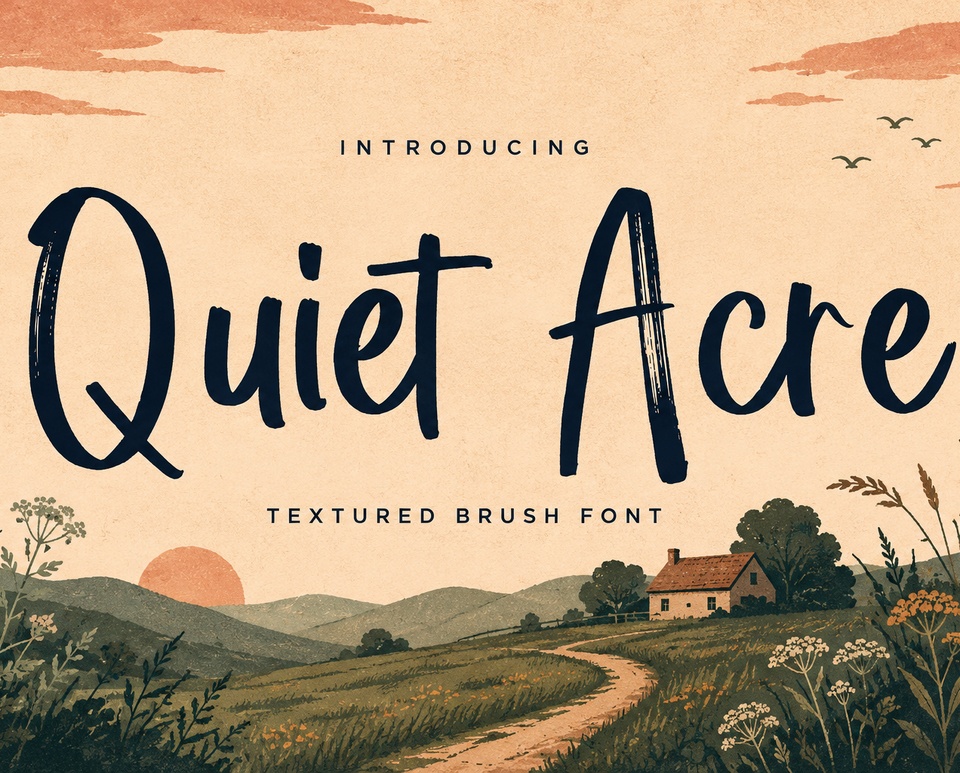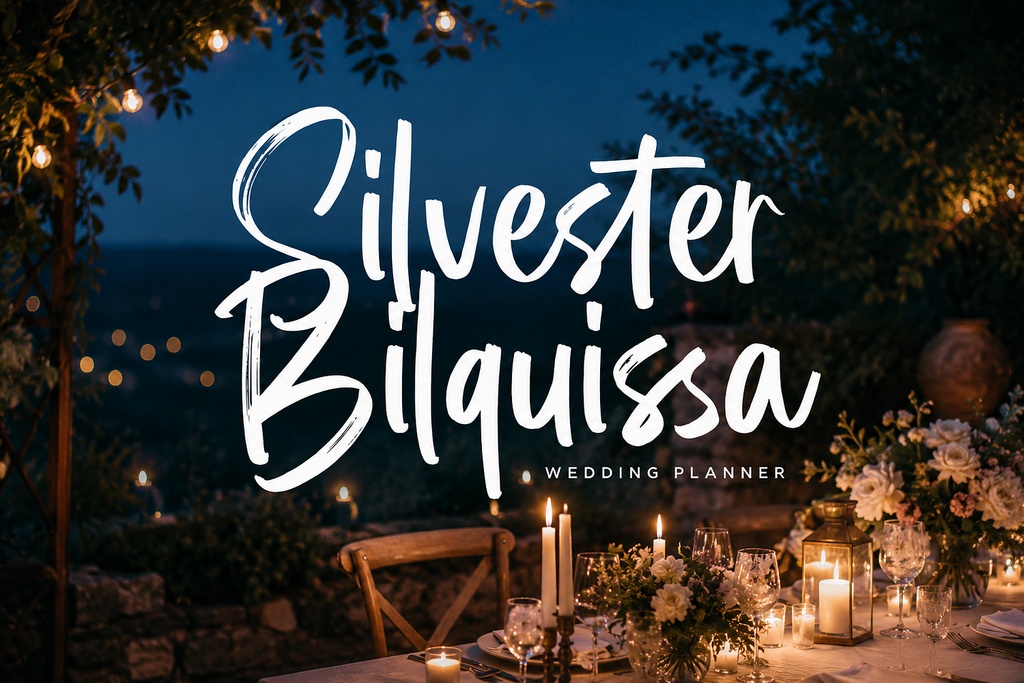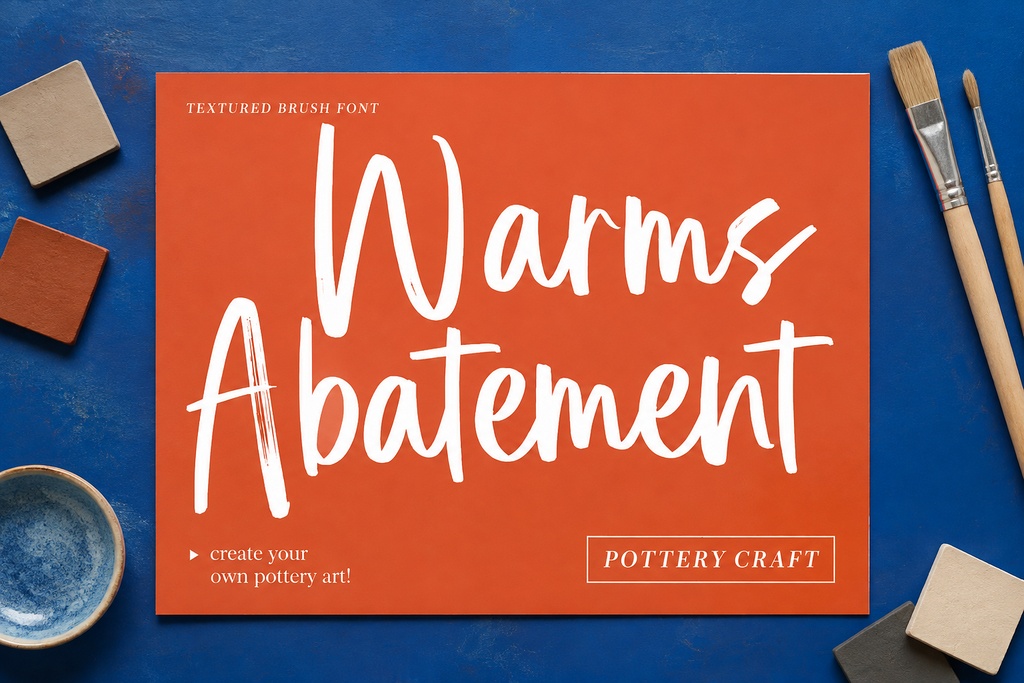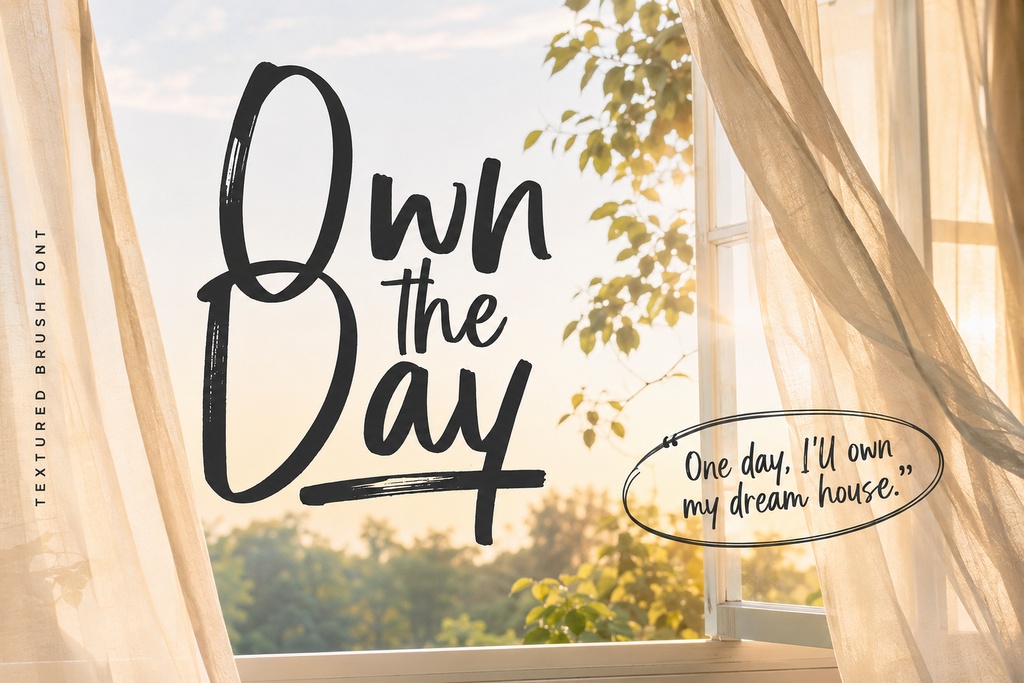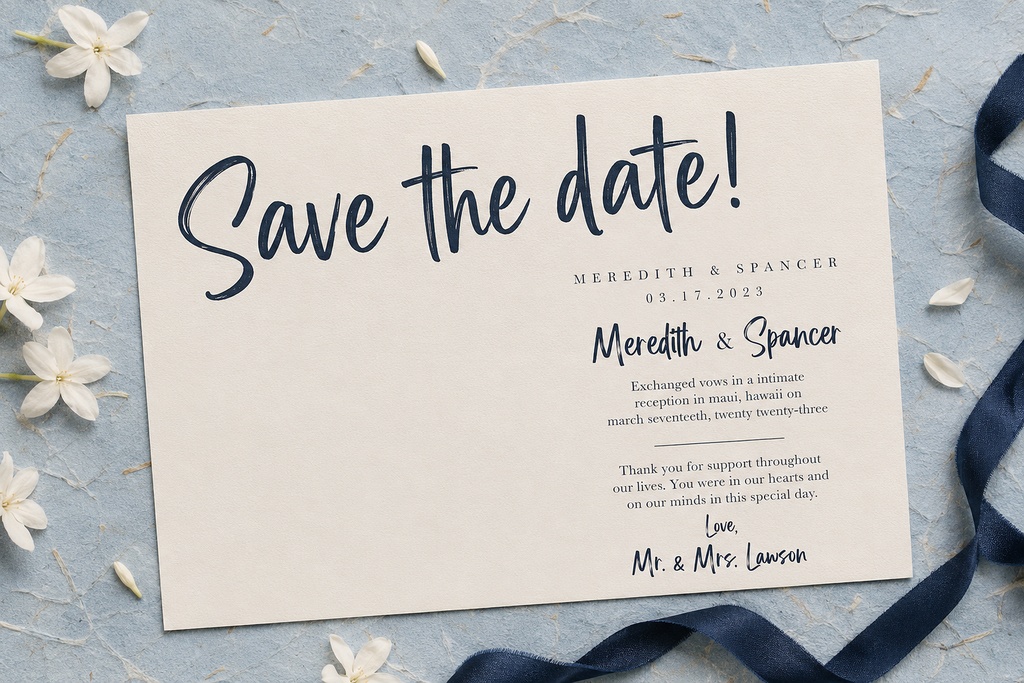
Quiet Acre — テクスチャードブラシディスプレイフォント
Quiet Acreは、ひと目で個性が伝わるデザインに適した、表情豊かで手触り感のあるテクスチャブラシ・ディスプレイフォントです。ラフなブラシの質感が、タイトル、ロゴ、パッケージ、プロモーション用アートワークに温かみと躍動感を加えます。短い単語やフレーズも視覚的に印象的に仕上げることができます。 **概要:** Quiet AcreはRegularスタイル1種類で提供されます。PaperMoon 2026 Commercial Proパッケージには、240個のグリフと243個のマッピング文字が収録されており、Basic Latin、Latin-1、およびLatin Extendedの1文字をカバーしています。標準的なOpenTypeの「liga」機能による標準リガチャに対応しており、対応アプリケーションでは、フォントに用意された置換によって文字の流れをより自然に見せることができます。個別のウェイトファミリーや、カーニング機能についての保証は含まれていません。 **主な特徴:** テクスチャ感のあるブラシレタリングは、ディスプレイサイズのタイポグラフィ、表現力豊かな見出し、印象に残るワードマークに適しています。対応ソフトウェアでは、OpenTypeの「liga」機能を使用して標準リガチャを利用できます。4種類の実用的なファイル形式を収録しています。デスクトップデザイン向けのOTF、幅広いデスクトップ環境に対応するTTF、Webプロジェクト向けのWOFF、そして最新のWeb環境に適したWOFF2です。Regularの1スタイル構成により、Quiet Acreはアクセントフォント、見出し用フォント、コンパクトなブランディング素材として手軽に使用できます。 **用途:** この手書きブラシフォントは、ロゴデザイン、商品パッケージ、店舗ラベル、ブランディングシステム、雑誌・エディトリアルの見出し、SNSグラフィック、ポスター、キャンペーン用アートワーク、写真やイラストを背景にした印象的な文字表現などにおすすめです。有機的なディスプレイスタイルは、ウェディングペーパーアイテム、招待状、メニュー、サイン、アパレルグラフィック、名言・引用デザインなど、手作り感のあるビジュアルが求められるさまざまなプロジェクトにも適しています。長文の段落や小さなインターフェーステキストに使用する場合は、より控えめな書体と組み合わせ、最終的な表示サイズでの可読性を確認してください。 **対応形式と収録ファイル:** ダウンロードには、Quiet Acre-Regular.otf、Quiet Acre-Regular.ttf、Quiet Acre-Regular.woff2が含まれています。OTFとTTFは、これらのフォント形式をサポートするデスクトップアプリケーションでの使用を想定しています。WOFFとWOFF2は、Webフォントファイルに対応した環境でのWebフォント実装向けに提供されています。OpenTypeリガチャの動作は、使用するアプリケーションの機能や設定によって異なります。収録文字セットはBasic Latin、Latin-1、およびLatin Extendedの1文字として明確に定義されており、幅広い多言語、ギリシャ語、キリル文字への対応は保証されていません。 **ライセンス:** クライアントワーク、有料ブランディング、パッケージデザイン、エディトリアル、広告、販売用製品などの商用プロジェクトには、Cubebrush Commercialライセンスを選択してください。Commercialライセンスを標準的に推奨しており、クレジット表記は必要ありません。Basicライセンスは、1人のユーザーによる個人的かつ非商用のプロジェクトにのみ使用してください。フォントファイルを配布したり、製品に埋め込んだりする前に、Cubebrushの最新のライセンス規約を確認してください。フォントファイルを単独の素材として再配布したり、フォントライブラリへアップロードしたりすることは禁止されています。 Quiet Acreで、次の見出しやワードマークにドライでエネルギッシュなブラシテクスチャを加えてみましょう。